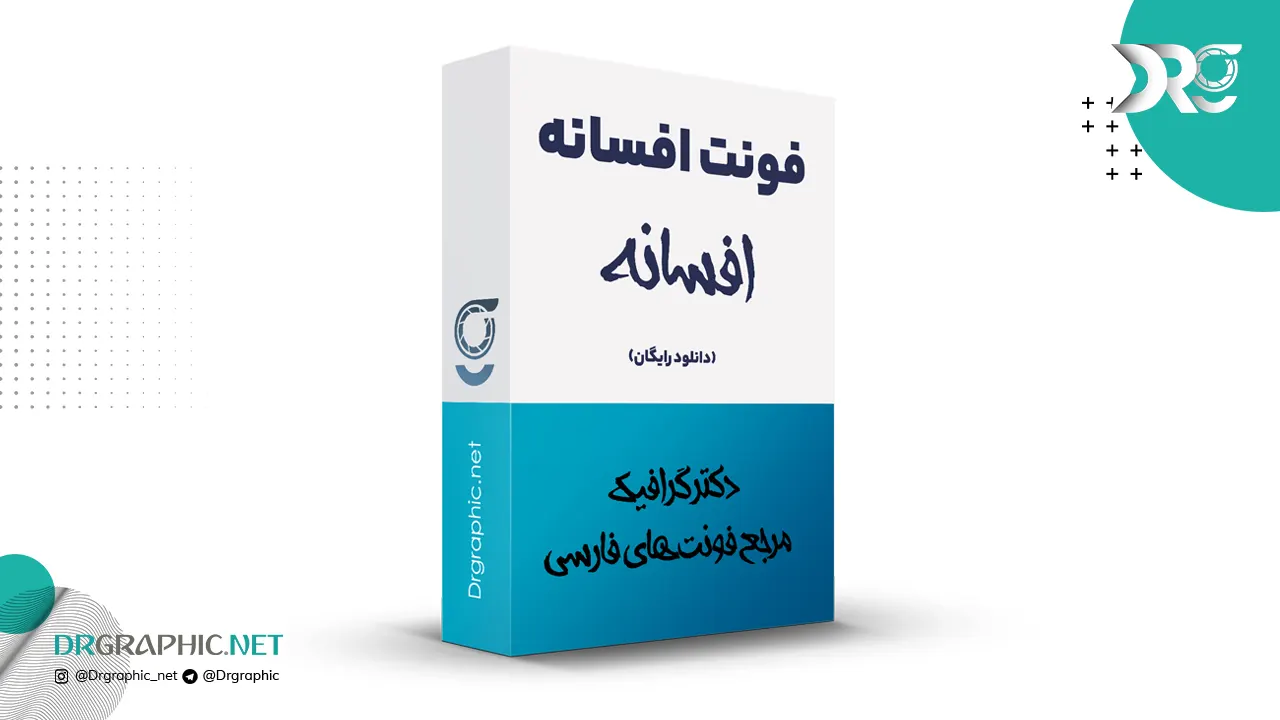
دانلود فونت فارسی افسانه Afsaneh
فونت فارسی افسانه – AFSANEH font از جمله فونتهای می باشد که در طراحی آن از سبک خاصی استفاده شده است که باعث شده این فونت جذاب و پرکاربرد شود که در طراحی گرافیک کاربرد بسیار خوبی دارد.
فونت فارسی افسانه یک فونت فانتزی می باشد .